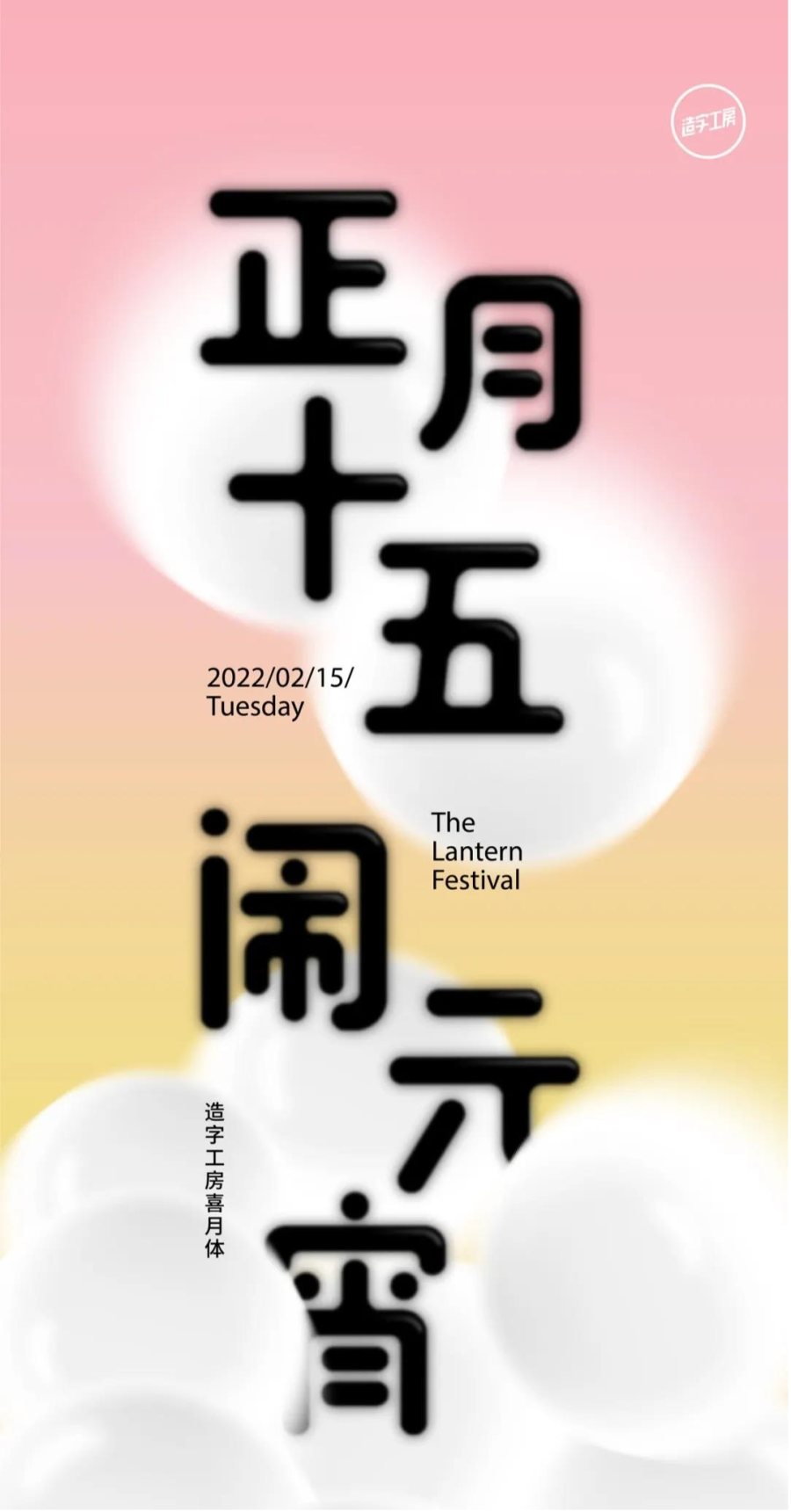
造字工房喜月体,其字形大小不一、参差错落,造型或倚或正,或重或轻,笔画恣意洒脱、率真拙朴,随性又不拘谨,妙趣横生。此款字体适用于书籍、报刊杂志标题、电视字幕、广告设计等视觉环境,有着极强的应用空间。本字体为简体字库,采用OpenType/CID格式,Adobe-GB1-5编码。基于中华人民共和国GB2312-80字符集标准,另按需添加101个汉字。共收容字数6864CJK汉字,ASCII常用字符100个。